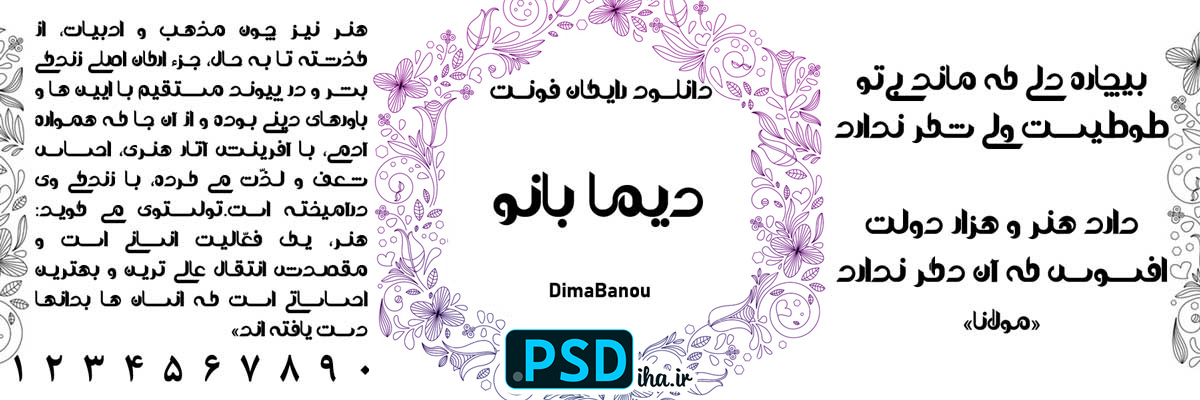
فونت دیما بانو
فونت دیما بانو – ظرافت و حس زنانه در طراحی
اگه پروژه‌هاتون حال و هوای زنانه، ملایم و لطیف داره – مثل کارت ویزیت آرایشگرها، بروشور فروشگاه لباس زنانه، دعوتنامه مراسم تولد یا منوی کافه‌های شیک – فونت دیما بانو دقیقاً همون چیزیه که نیاز دارید. انحناهای نرم و فاصله حروفش طوری طراحی شده که حس صمیمیت و ظرافت رو بدون شلوغ کاری منتقل کنه. من خودم توی طراحی لوگوهای فمیلی و بلاگرهای حوزه مد و زیبایی بارها ازش استفاده کردم و نتیجه همیشه رضایت‌بخش بوده.